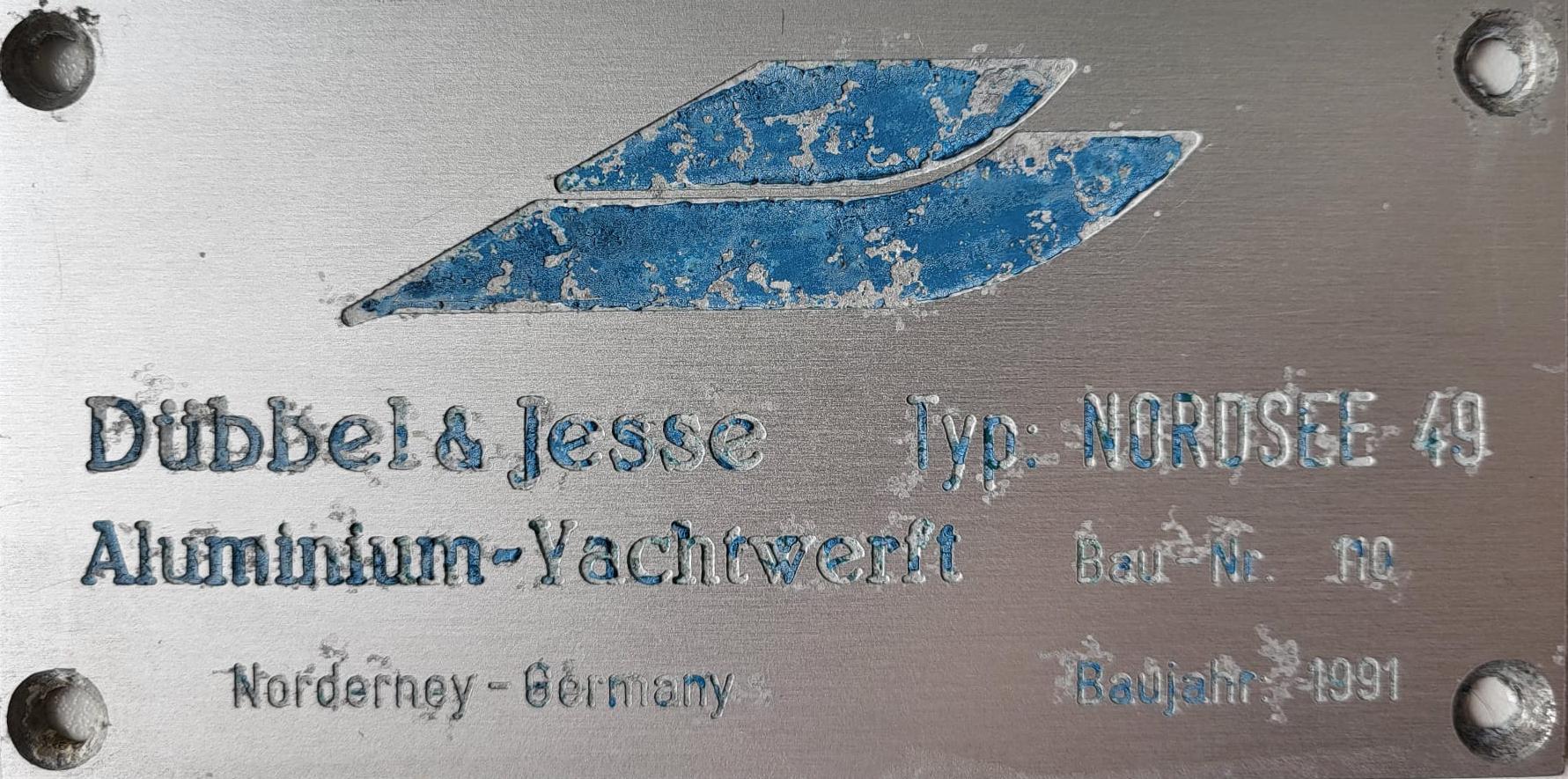
Suche Schrift von Dübbel und Jesse (ca. 1991)
ich habe jetzt alle gängigen Schriftensuchseiten durch und finde die Schrift von dem Schild nicht.
Das Schild wird wohl um 1991 gefertigt worden sein und stammt von einer Yacht, das von Dübbel und Jesse gebaut worden ist.
Es geht um die Zeilen "Dübbel & Jesse Aluminium-Yachtwerft"
Mir kommt die Schrift so bekannt vor, aber wahrscheinlich wurde durch das Fräsen diese so verfälscht, dass ich zu keiner Ergebnis komme. Die Vorlage ist auch nicht mehr die Beste.
Geht schon in die Richtung, aber leider noch zu unähnlich 😕
Ich werfe einfach mal noch folgende Alternativen mit „schrägem“ e in den Ring:
Mir ist natürlich bewusst, dass das alles nur mäßige Kompromiss-Lösungen sind. Aber erstmal besser als gar nichts, oder?
In einem anderm Logo wurde die Souvenier verwendet.
Ich werde mal zusehen, dass ich aus den vorgeschlagenen Schriften was zusammenbastel.